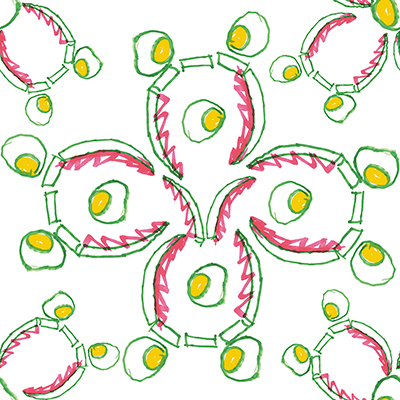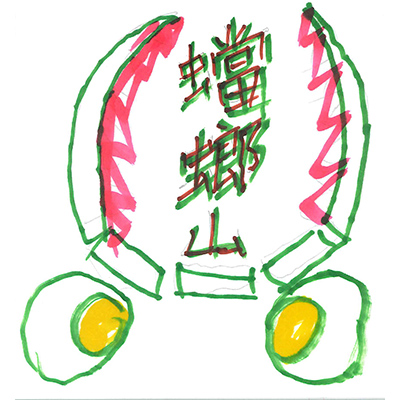
カマキリ花咲く
カマキリの顔が花に?目玉焼きに?
Artist姫蟷螂
Designer乙牧 和宏
Organization株式会社テクノヒューマンキャピタルラボ
カマキリの花?、目玉焼き?、面白いように変化するパターン作成、こうした楽しい作業を進めながら腕をアップしていく?。(姫蟷螂)
コミカルなカマキリの表情や姿を切り取り、サークル状に構成しました。回転するリズムの中に、新しい発見があり、人と人を繋いでいくコミュニケーションの輪の表現でもあります。(乙牧 和宏)
コミカルなカマキリの表情や姿を切り取り、サークル状に構成しました。回転するリズムの中に、新しい発見があり、人と人を繋いでいくコミュニケーションの輪の表現でもあります。(株式会社テクノヒューマンキャピタルラボ)